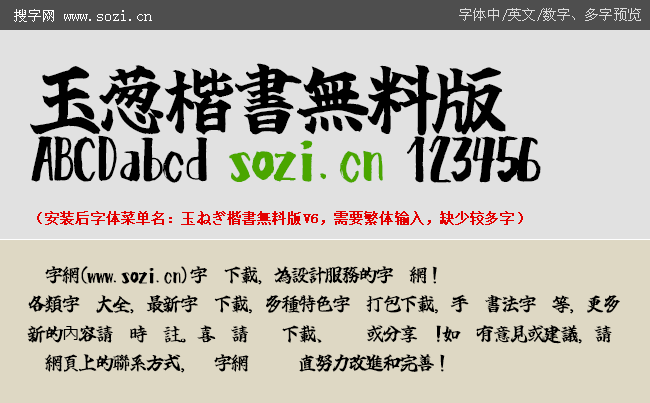
玉蔥楷書無(wú)料版
搜字網(wǎng)給大家提供一款玉蔥楷書無(wú)料版手寫體字體下載,玉蔥楷書無(wú)料版是一款日文的手寫風(fēng)格書法字體,字體粗壯有力,簡(jiǎn)潔大方,十分醒目,因?yàn)槭侨瘴淖煮w,所以需要繁體輸入,并缺少部分文字。適合應(yīng)用于藝術(shù)設(shè)計(jì)、平面宣傳設(shè)計(jì)、標(biāo)題設(shè)計(jì)、海報(bào)設(shè)計(jì)等應(yīng)用。